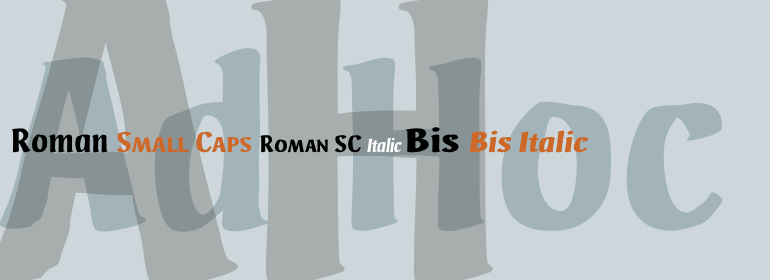
Ad Hoc™
字体品牌: Linotype(Monotype) 设计师:Luin,Franko 字体分类:衬线体 字体属性:外文 字符集:Unicode 发布时间: 2018
Ad Hoc is a fake. My intention was to design a typeface with the looks of the characters drawn on paper with a marker pen. But they are all drawn on a monitor, with no scanner ever involved. That's the reason why they look so regular.
Ad Hoc is Latin and stands for, approximately, for this reason". The expression itself is often used for something unplanned, improvised.
Ad Hoc was released in 1992.